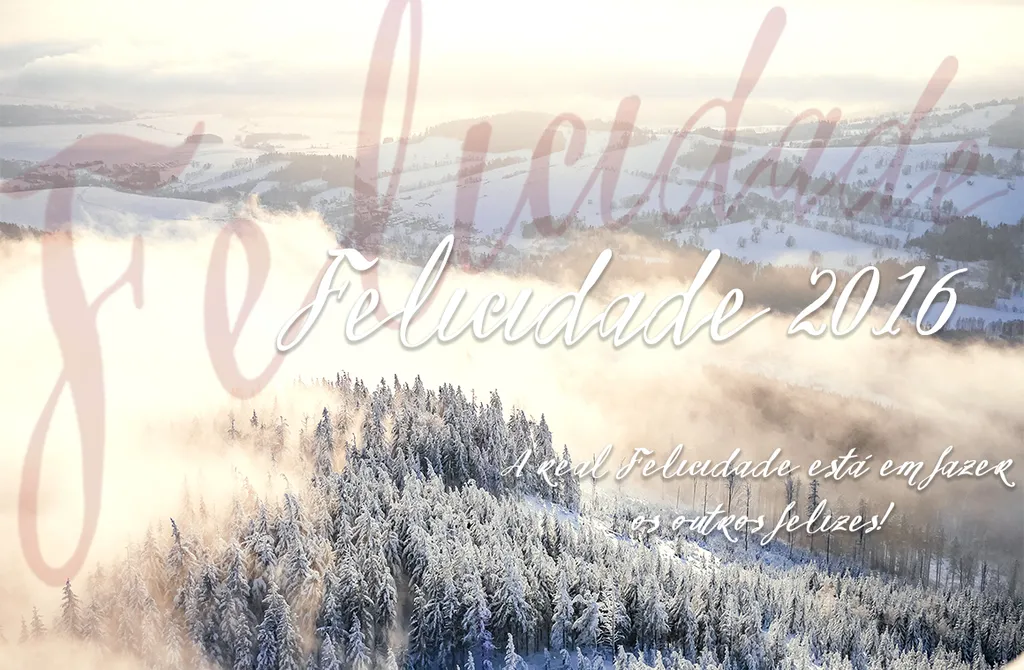
A Vtks Felicidade 2016 é uma fonte em estilo minúsculo que transmite alegria e encanto à qualquer projeto de texto. Ela tem origem na mão do designer Hamilton, oferecendo um visual amigável perfeito para elementos decorativos ou textos comuns no seu site ou aplicativo. Suas linhas fluidas e desenho elegante fazem-a uma escolha ótima para adicionar personalidade à sua marca. É perfeita para nomes de empresa, logotipos, banners de promoção ou qualquer outro uso comercial que deseje agregar um toque especial ao seu material digital. Com a Vtks Felicidade 2016 Font, você pode garantir o uso comercial deste estilo único e encantador. Para adquiri-la, siga este link para adquirir uma licença em dólares americanos. Seja parte desta história de encanto, enriqueça seus projetos com a Vtks Felicidade 2016 Font.